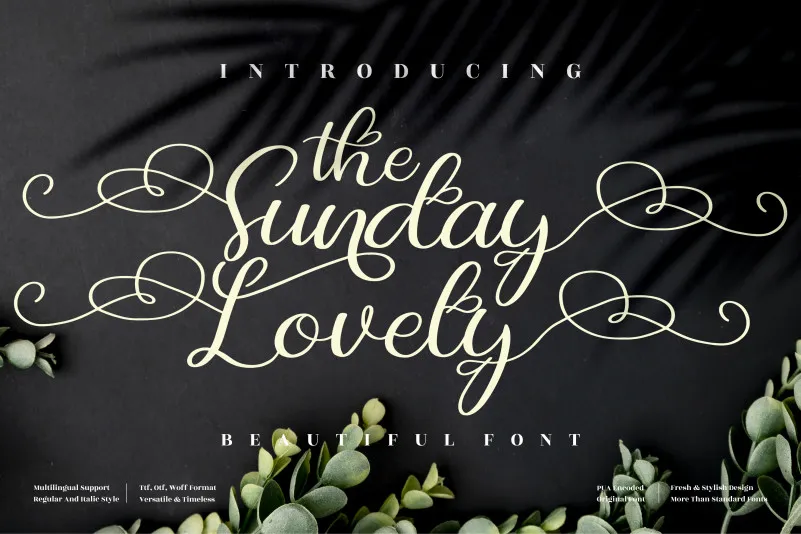
The Sunday Lovely Font – Download Grátis
A fonte The Sunday Lovely é uma chamada romântica perfeita para qualquer projeto que deseje trazer uma pitada delicada e encantadora ao seu trabalho, seja ele uma marca de empresa ou um desenho de móveis de casa. Suas linhas finas e traços suaves a tornam ideal para criações tão variadas quanto lindos cartões de nome, etiquetas de embalagens de produtos e até mesmo capas de livros. A fonte é perfeita para aqueles momentos especiais onde a delicadeza da letra faz toda a diferença – seja em uma decoração de festa ou uma camisa personalizada com mensagens amorosas. Com suas formas elegantes, The Sunday Lovely se torna um complemento perfeito para sua paleta de recursos gráficos. A fonte é especialmente adequada para criar identidades visuais, tags em produtos, cartões de convite e até mesmo marcas de imagem personalizadas que deixarão seu trabalho com um toque especial. Seja criando uma capa de livro ou adicionando um texto agradável em etiquetas de presentes, The Sunday Lovely trará sofisticação ao design sem perder o encanto simples e suave característico da fonte.